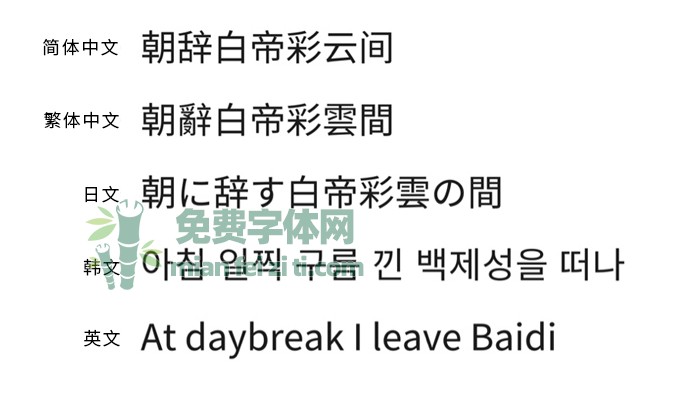
中文字体特刊:思源黑体
介绍
思源黑体重心置中、字面稍大,是一款给人感觉较为轻松友善的现代黑体。它是由Google和Adobe共同开发,是一款多语言字体,致力于为亚洲用户提供愉悦的阅读体验。该字体支持中文简体、中文繁体、日文和韩文四种亚洲文字,共计支持44666个文字的65535个字形。目前有两个版本:
1. Google版:官方名称为Noto Sans CJK,是Google的Noto字体家族的成员。
2. Adobe版:官方名称为Source Han Sans,是Adobe的Source字体家族成员。
轶事
众所周知,思源黑体是Google的Noto字体家族成员。Noto是『No Tofu』的简称,在Windows系统中,无法显示的字符会以"□"代替,日本人称之为Tofu,即"豆腐"的意思。由此可见,Noto字体家族的目标就是消灭"豆腐",也就是没有不支持的文字。